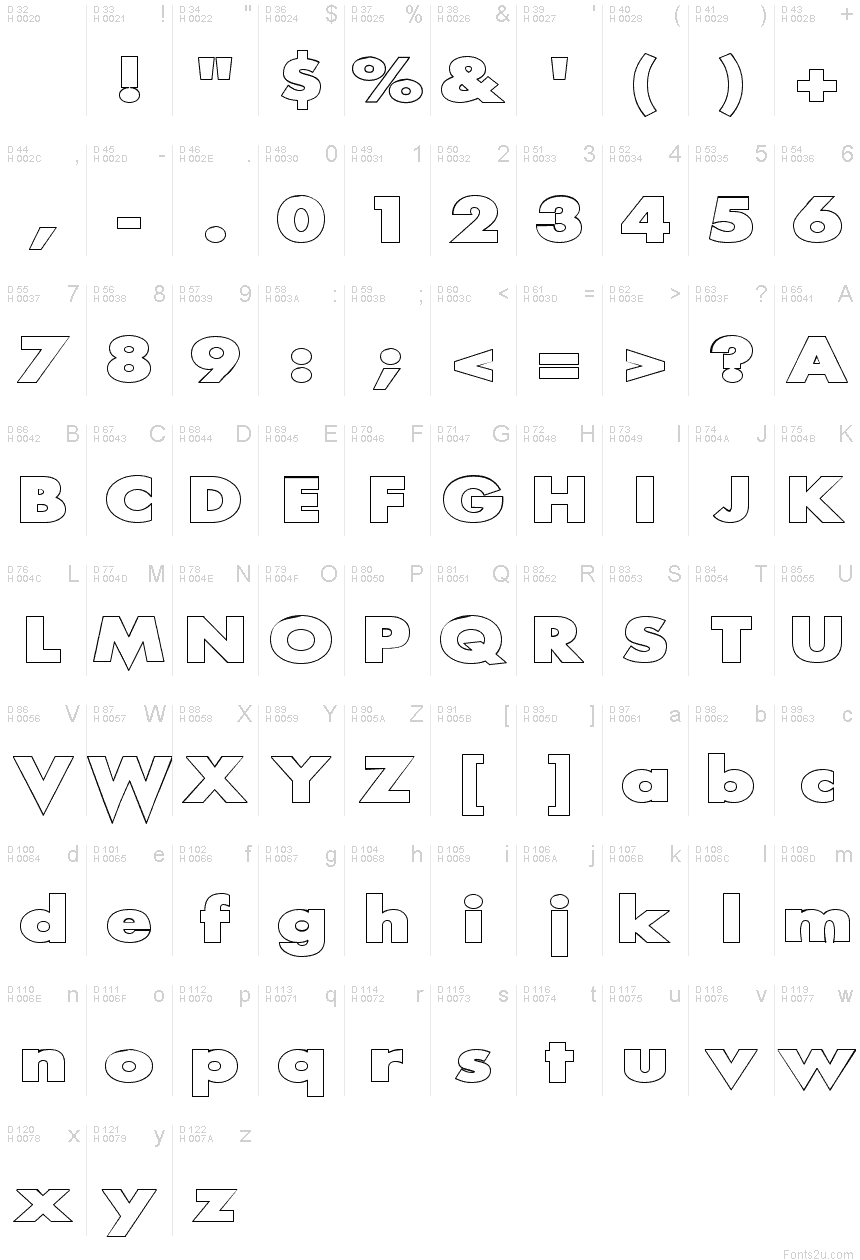
Scream Outlined, die kostenlose, konturierte Sans-Serif von Samuel Park, die auf dem Logo der Scream-Filme basiert, verwandelt weiche, aufgeblähte Buchstaben in etwas Unbehagliches und Filmisches. Die dicke Kontur und die abgerundeten Formen wirken auf den ersten Blick stumpf und zugänglich, doch die übertriebenen Kurven und die kompakte, plakative Wirkung sorgen für die Slasher-Stimmung der späten 90er-Jahre.
Diese kostenlose Schrift eignet sich perfekt für Horror-Poster, Halloween-Flyer, Streaming-Thumbnails, VHS-inspiriertes Packaging und Movie-Night-Titel, bei denen der Genre-Bezug wichtiger ist als Perfektion. Sie funktioniert auch hervorragend für kurze Cover-Texte und Logo-Designs, da die breiten Umrissbuchstaben als kräftige Silhouette überzeugen, ohne ihren verspielten Gruselfaktor zu verlieren.
Based on the Scream films logo. Samuel Park -99
Scream outlined